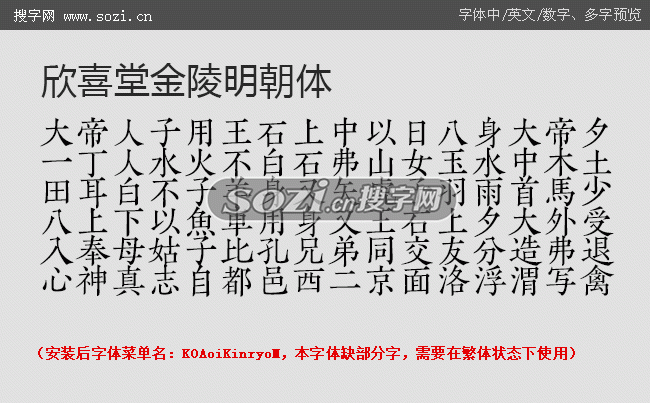
欣喜堂金陵明朝體—KOAoiKinryoM
搜字網(wǎng)提供一款欣喜堂金陵明朝體日系中文字體下載,欣喜堂金陵明朝體是一款非常漂亮的宋體字體,字體端正大方,整體效果非常出色,能夠應(yīng)用于平面設(shè)計(jì)、名片設(shè)計(jì)、廣告創(chuàng)意、印刷等場(chǎng)合應(yīng)用。